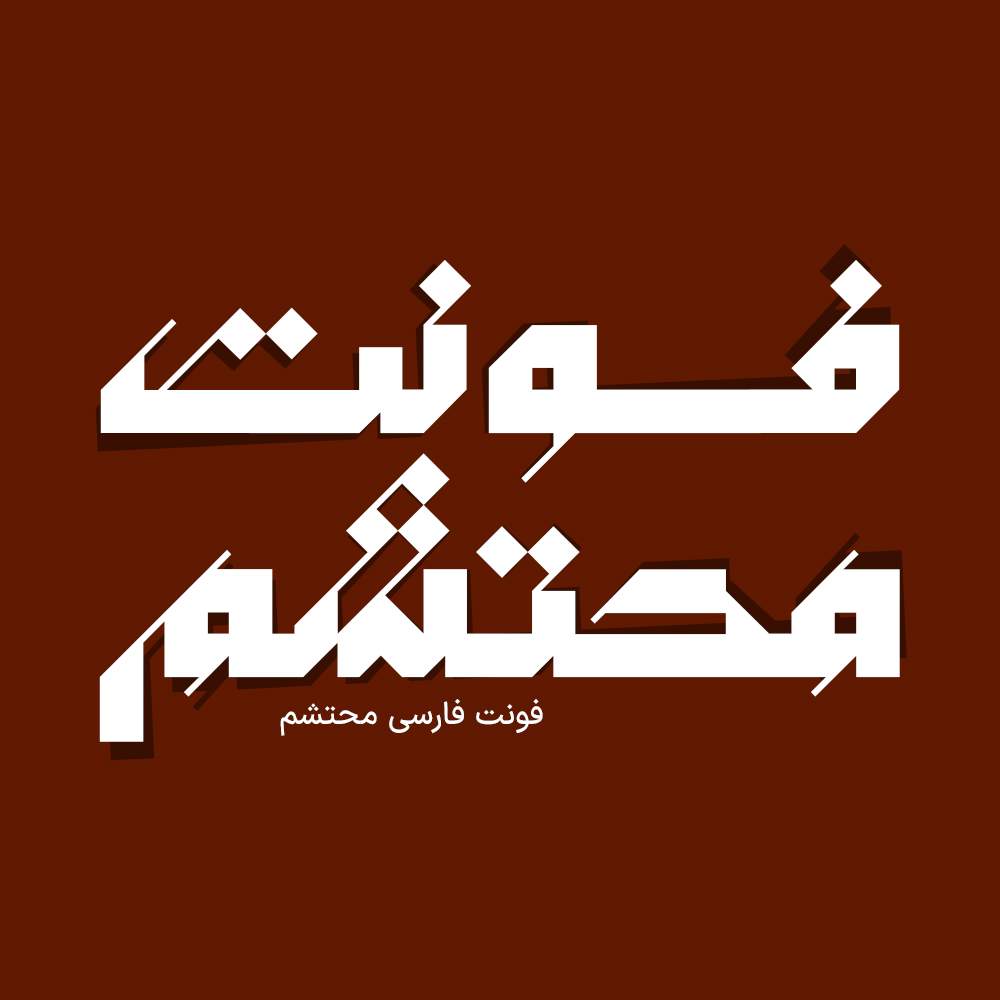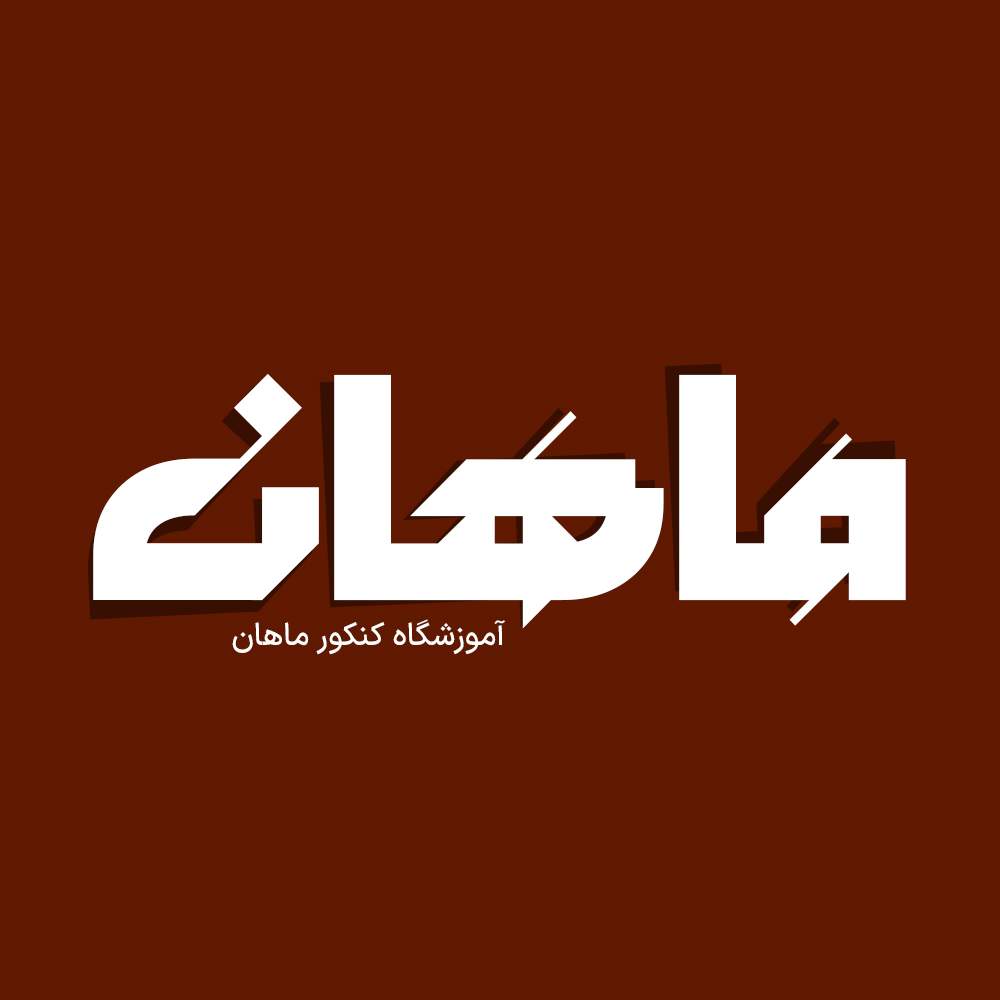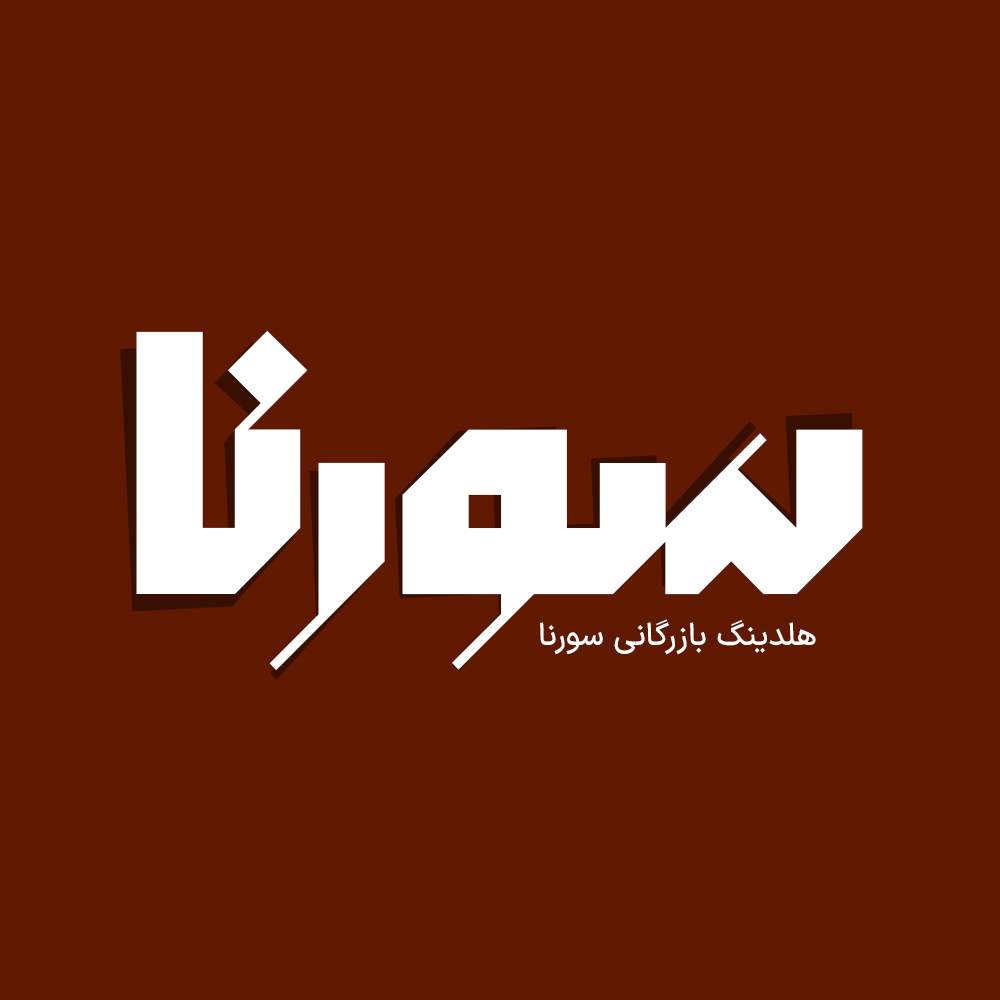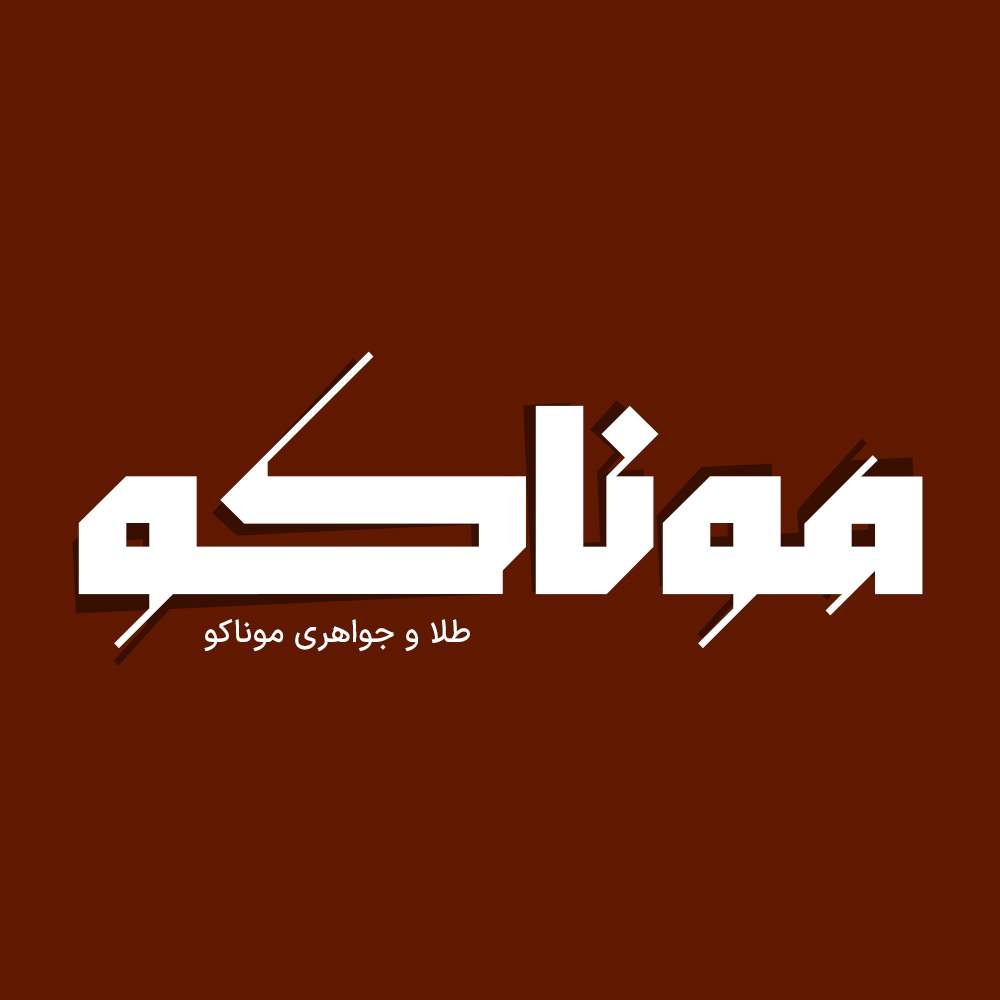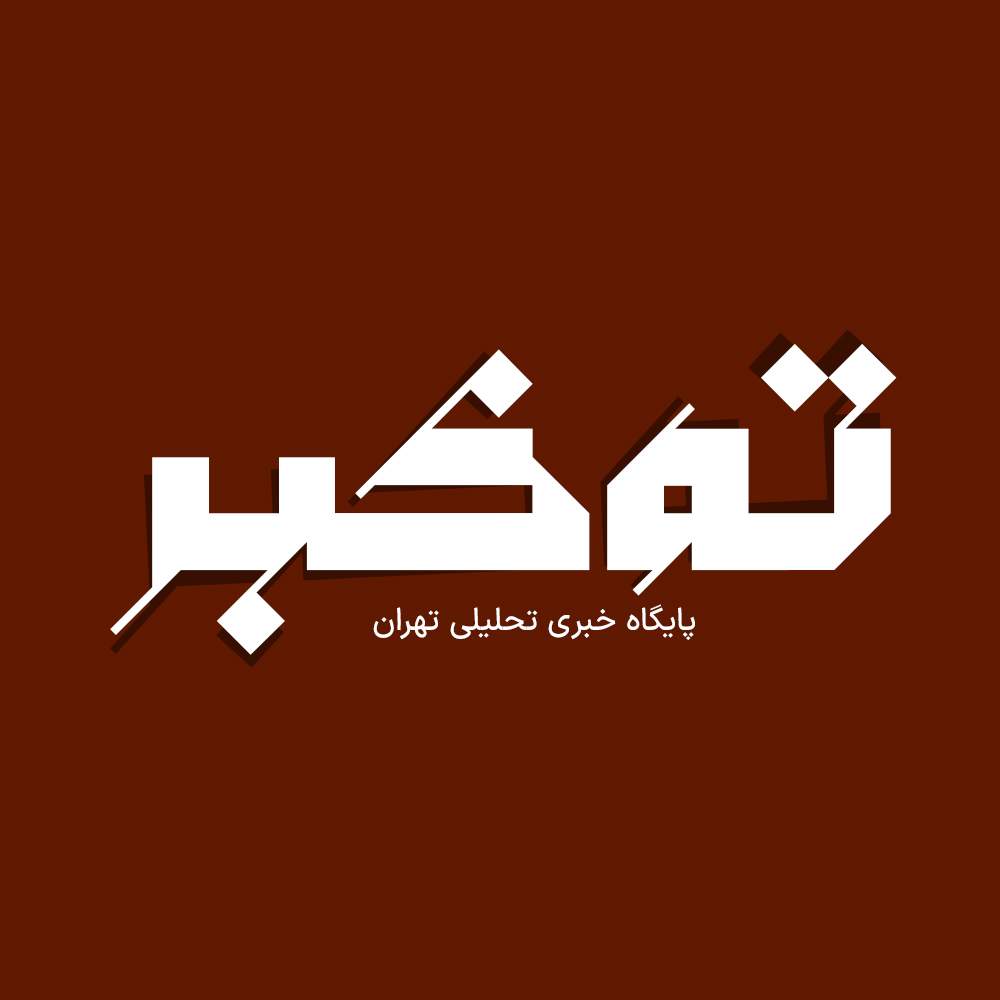
فونت فارسی محتشم Mohtasham Font
فونت فارسی محتشم یک فونت تک وزن با کاربرد طراحی لوگوتایپ و طراحی های مختلف همچون کتاب و تولید محتوای متن های کوتاه و عناوین می…
فونت فارسی محتشم یک فونت تک وزن با کاربرد طراحی لوگوتایپ و طراحی های مختلف همچون کتاب و تولید محتوای متن های کوتاه و عناوین می باشد. این فونت با ساختار حروف خود مناسب استفاده در لوگوهای نوشتاری می باشد. همچنین از این فونت در طراحی تابلوهای چلنیوم هم به دلیل ساختار منحصر به فردش می توانید استفاده کنید. در ادامه برای شما نمونه تایپ های این محصول حرفه ای رو آماده کردیم که میتونید مشاهده کنید.
پیشنمایش و نمونه تایپ های فونت محتشم